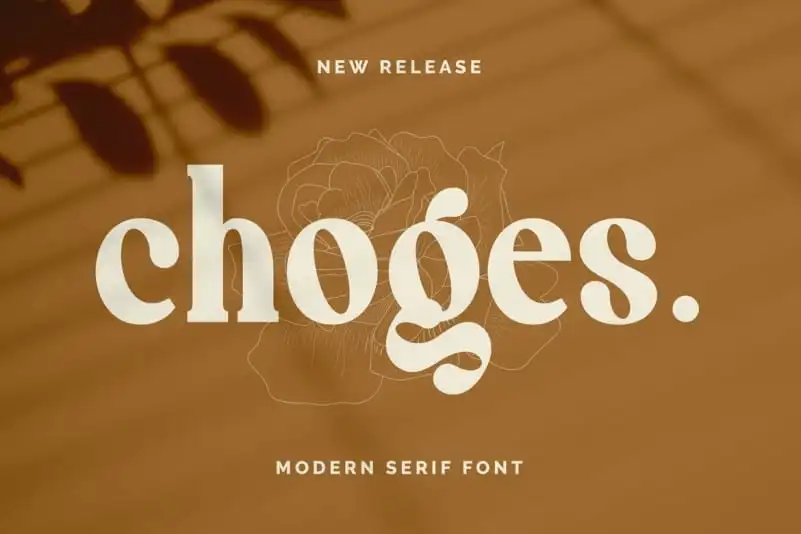
Esta fonte Serif é uma criação encantadora do designer FallenGraphic Studio que transborda elegância para uso em marca ou logomarca. Choges traz uma sensação moderna e marcante, carregada de ligaturas e alternativas que farão sua apresentação ou logomarca ainda mais impressionante e chamativa! Além disso, Choges oferece suporte a múltiplas línguas e já está predefinida para uso com PUA (Propriedades Unicode Avançadas). Aproveite a oportunidade de dar um novo tom à sua identidade visual com Choges Serif Font.